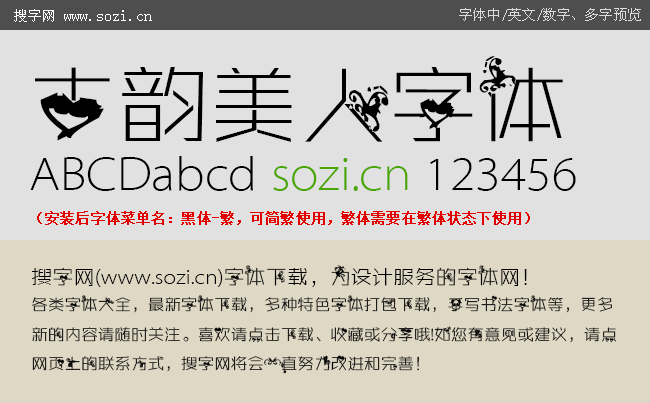
古韻美人字體
搜字網(wǎng)給大家提供一款很有趣的手機中文字體下載。修改者給他起了個古韻美人字體這么美的名字,這款手機字體在字體筆畫間插入了漂亮的蝴蝶和花紋圖案。真是趣味性實足的一款手機字體,該中文字體個性實足,趣味性強,又保持了文字的識別度,特別適合喜歡手機字體個性一些的朋友在手機上安裝使用。